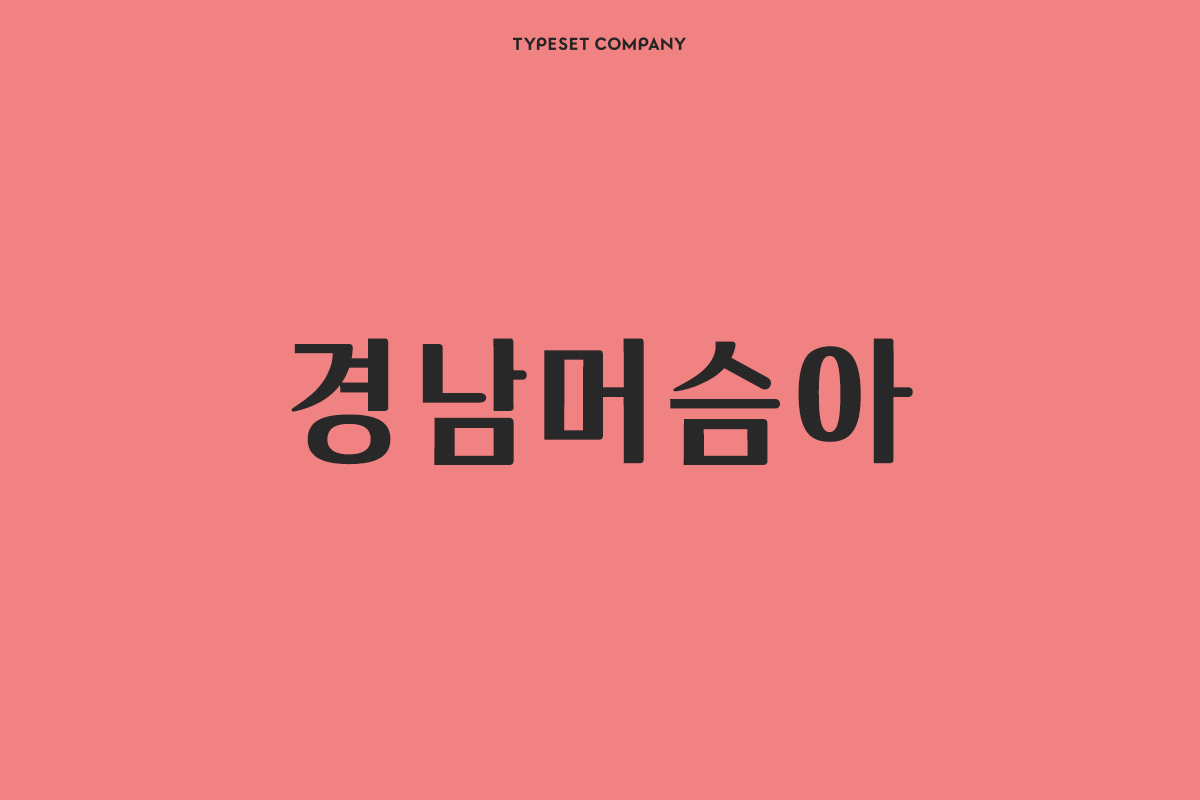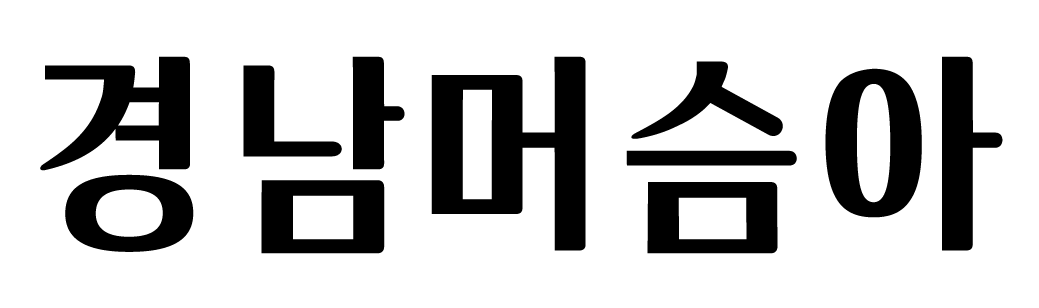
TSC경남머슴아
TSC경남머슴아 font in use
‘TSC 경남머슴아’는 고딕의 기본 형태에 특정 자소에서 명조의 삐침 형태를 볼 수 있는 고딕 폰트다. 딱딱하고 날카로운 경상남도 사투리를 쓰지만 곧은 마음을 가진 경남머슴아를 모티브로 제작되었다.
• 김성일 최미진